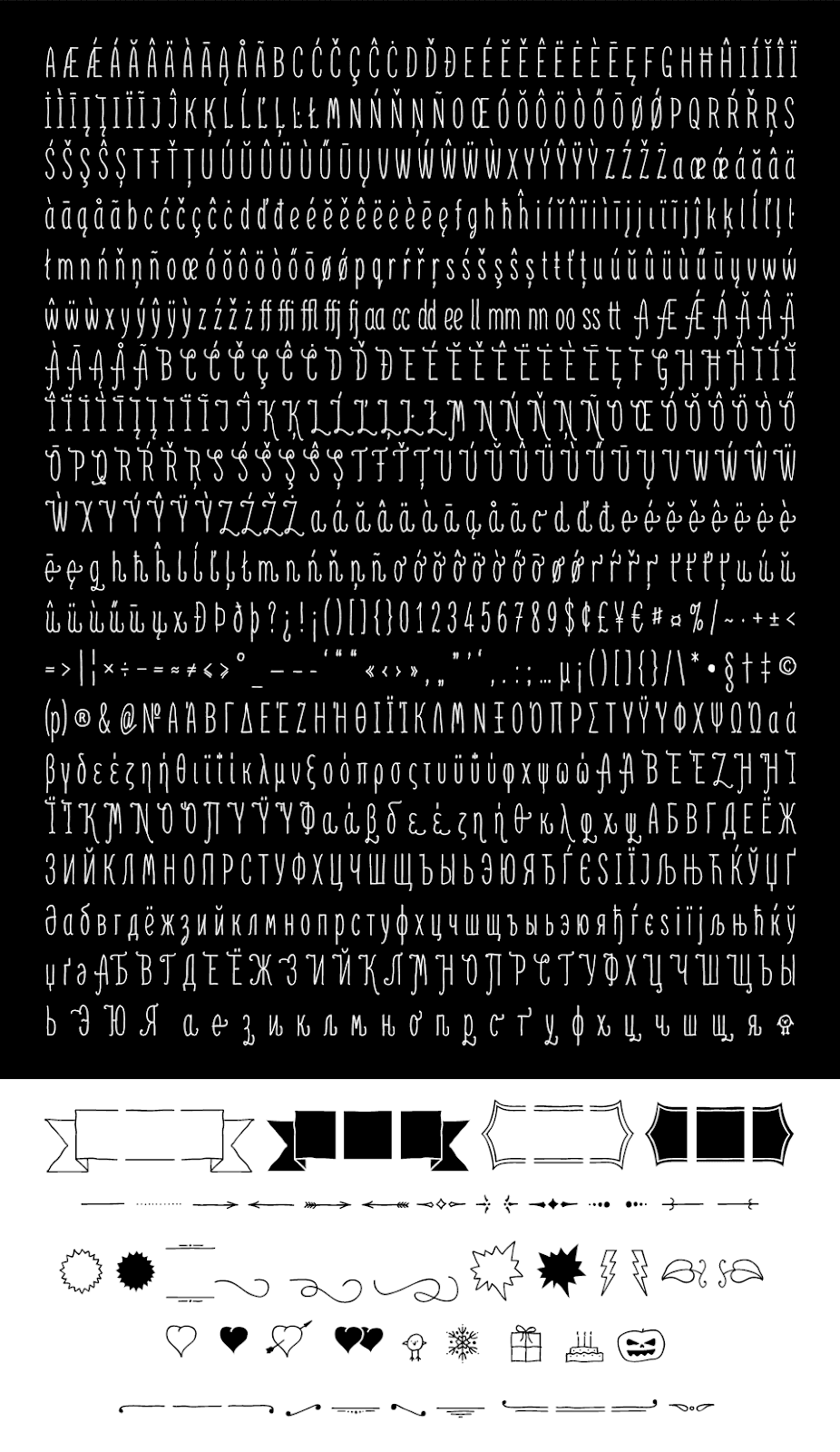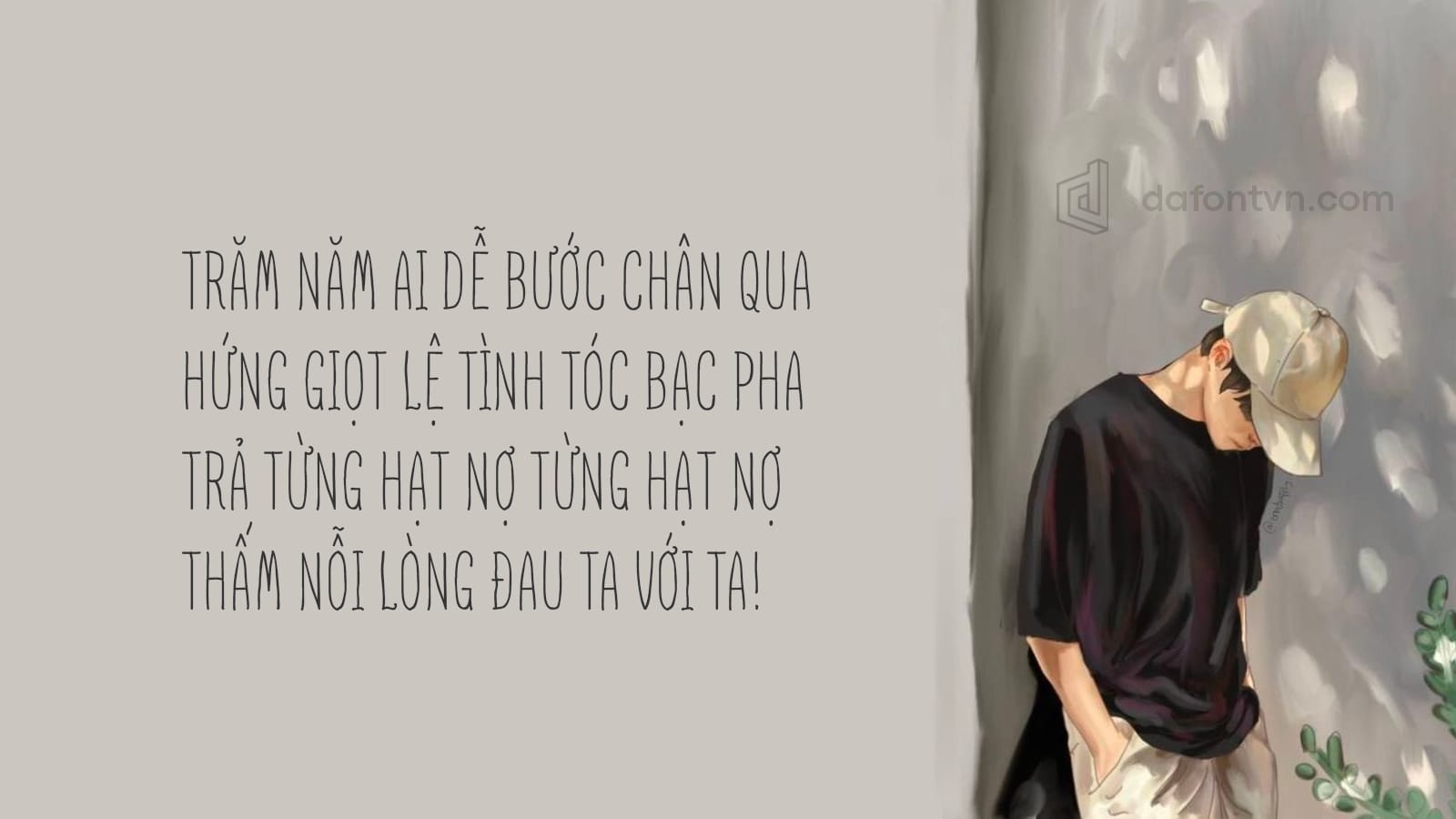
iCiel Finch Việt Hóa Việt hóa là một font chữ được thiết kế với những đường nét mảnh và thanh tựa như những chú chim đang bay trên bầu trời. Các nét chữ cũng giống các chữ viết tay phù hợp cho rất nhiều các thiết kế khác nhau. Font việt hóa đầy đủ 2 kiểu Regular, Bold và 1 font trang trí.